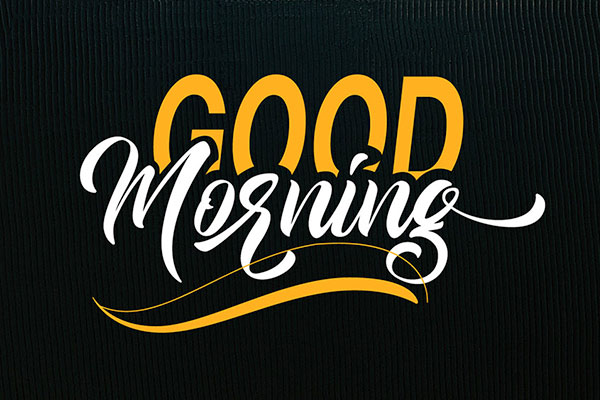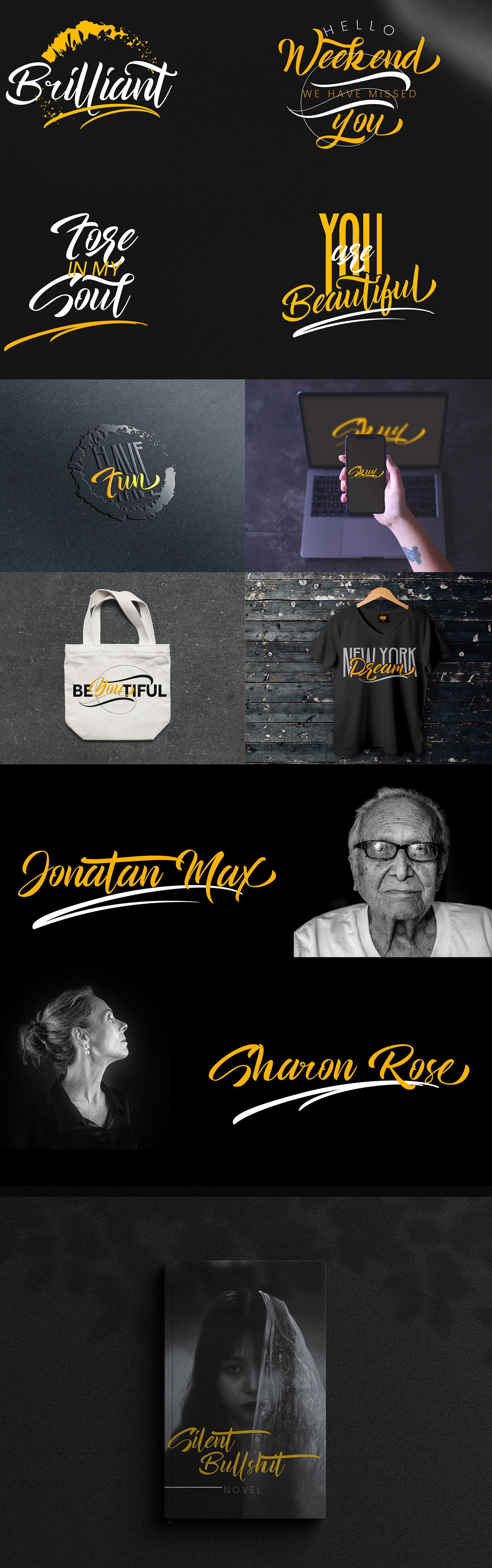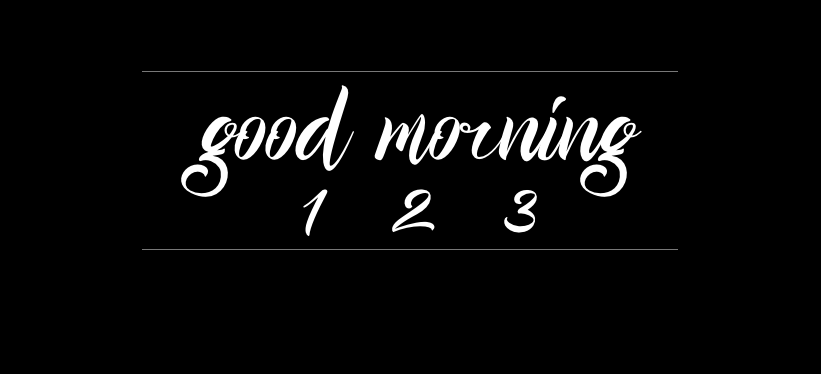
Good Morning
字体介绍
Good Morning的作者是来自印尼的设计师Khaiuns,这位设计师非常擅长手写体,创作了很多手写字体。Good Morning脚本字体是一种令人难以置信的甜美迷人的脚本,可以轻松为Khaiuns的下一个设计增添趣味!它包含大写,小写和符号。需要注意的是Good Morning字体为免费版,它的数字部分只包含了123三个字符(一般也用不上数字)。
GoodMorning字体非常适合用于品牌,邀请函,文具,婚礼设计,社交媒体帖子,广告,产品包装,产品设计,标签,摄影,水印,特殊事件或其他任何东西。
字体应用示例